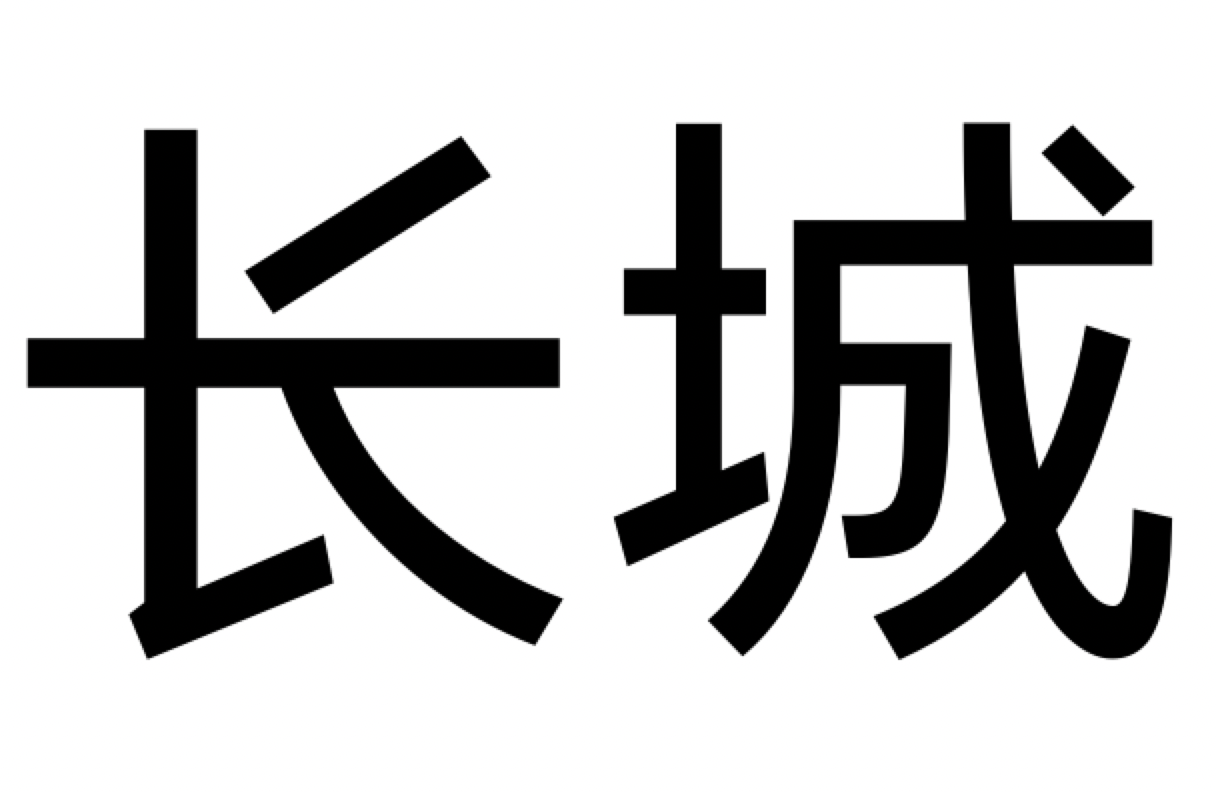
长城汽车
字体作为信息传递的重要载体,除了安全识别阅读,也兼并着美学设计。为解决多品牌、多车型场景下字体应用不统一带来的品牌形象碎片化问题,同时提升全球用户的驾驶阅读体验,长城汽车决定倾力打造一款适合车机屏幕阅读的字体。车载屏字体并非单纯追求美观,而是以安全为核心,兼顾品牌、技术和用户体验的系统化设计策略。这一举措反映了汽车行业从“功能驱动”向“体验驱动”的转变,也体现了中国品牌在细节创新上的深入探索。